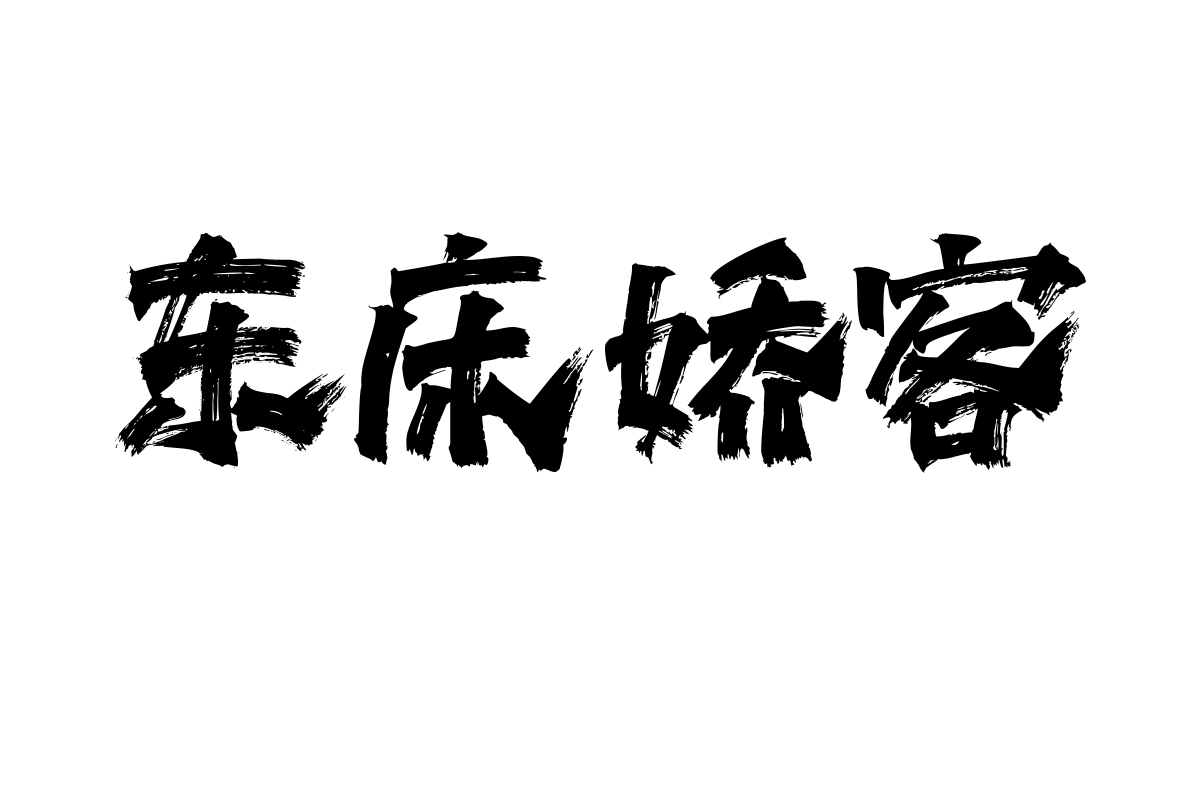
潮字社咏春八斩刀是一套以中国传统武术“咏春”为主题的字体,由潮字社设计。这套字体以其独特的书法风格和流畅的线条而受到广泛赞誉。
潮字社咏春八斩刀的字体特点如下:
1. 字形结构紧凑,线条流畅,富有动感。每个字都经过精心设计,使其既有美感又不失实用性。
2. 笔画粗细适中,易于书写。无论是初学者还是有经验的书法爱好者,都能轻松掌握。
3. 字体风格独特,融合了中国传统书法与现代设计理念。它既保留了传统书法的韵味,又融入了现代审美元素,使其更具时代感。
4. 适用于各种应用场景,如广告、宣传、包装等。无论是商业还是艺术领域,潮字社咏春八斩刀都能展现出其独特的魅力。
总之,潮字社咏春八斩刀是一款极具创意和实用性的字体,适合用于各种需要展示传统文化元素的场合。